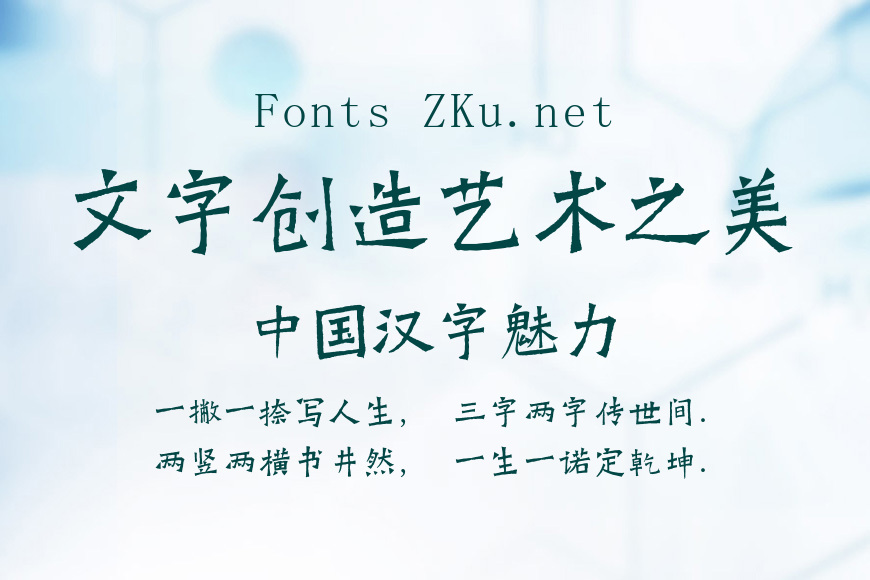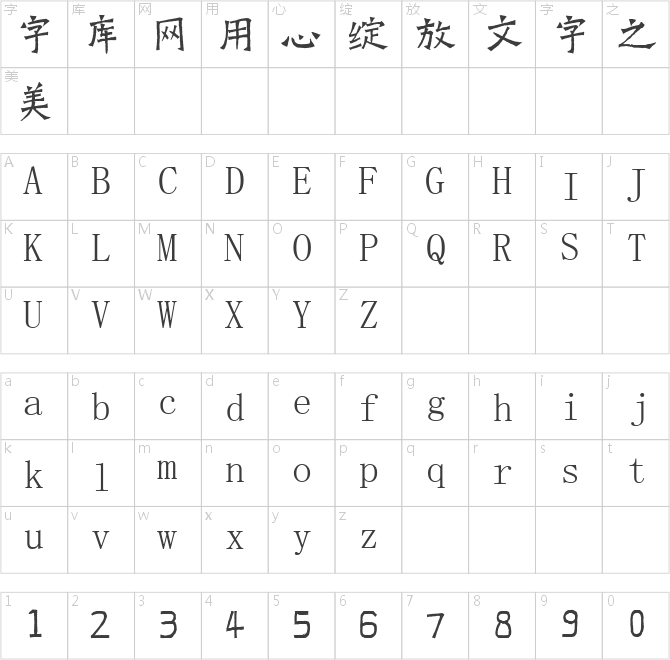
字体名称: 爨龙颜碑体
爨龙颜碑体
爨龙颜碑体介绍
爨龙颜碑体字体下载源自于云南陆良的爨龙颜碑字体
﹤p﹥﹤p﹥源自于云南陆良的爨龙颜碑字体,由篆刻书画家华松老师毛笔手写后制作成此爨体字库,开放给喜爱书法字体的人们使用。(注:本次上传的字体库补录了一些之前缺失的字)﹤/p﹥﹤/p﹥
爨龙颜碑体字体源自于云南陆良的爨龙颜碑字体字库是一款让人赏心悦目、百看不厌的中文字体,适合各类广告和产品包装设计应用,字体大小30.16MB,格式为ttf字体,上传用户是刀老师做包装?,作者/版权方为华松